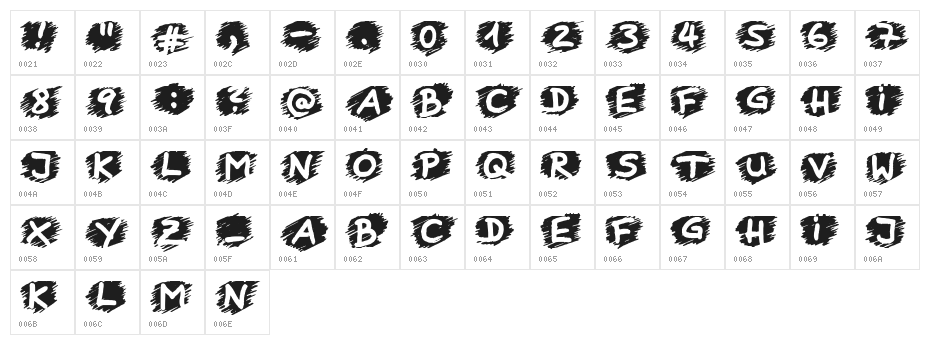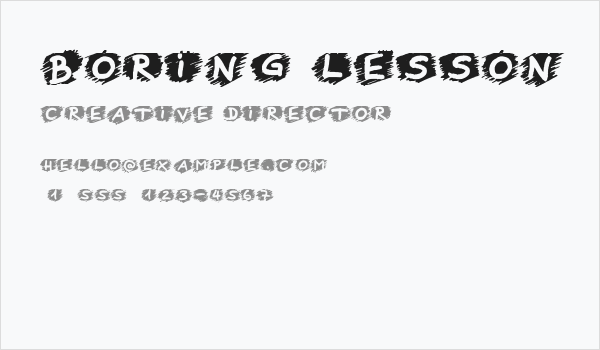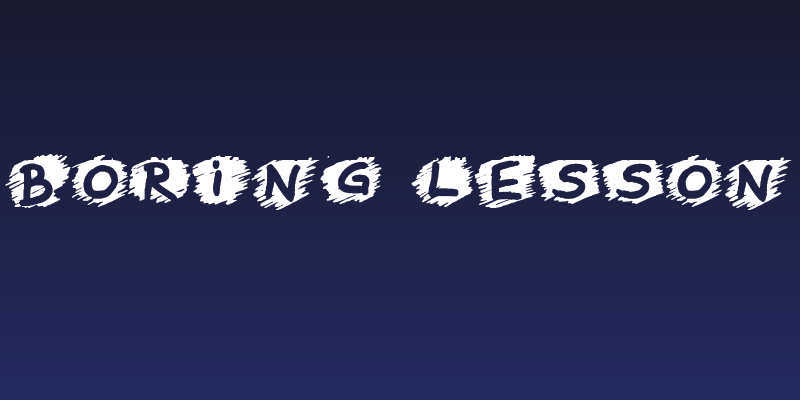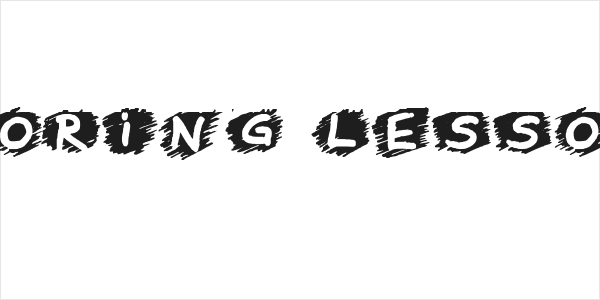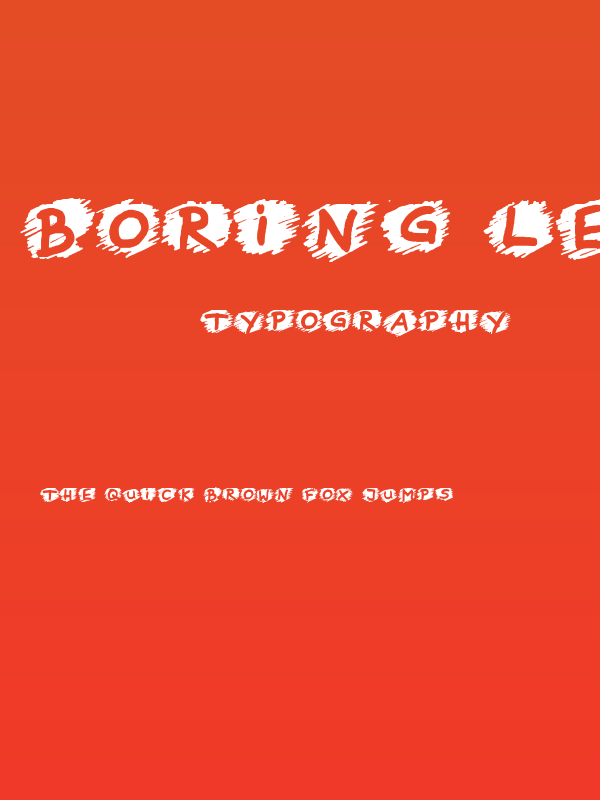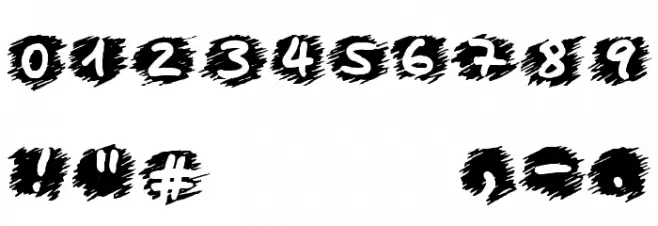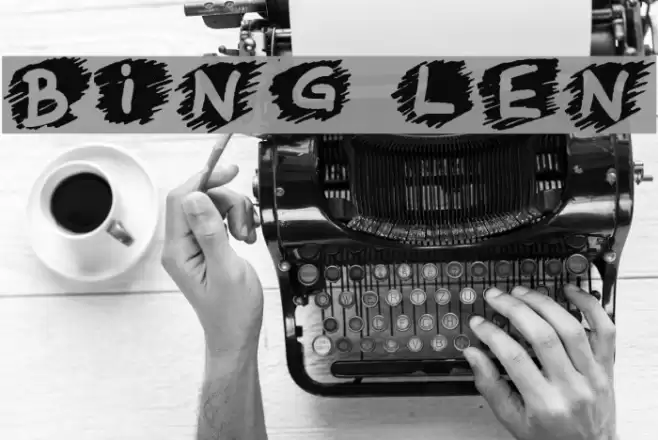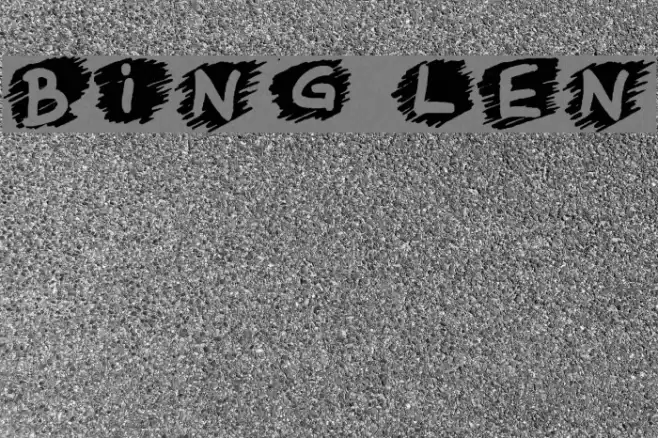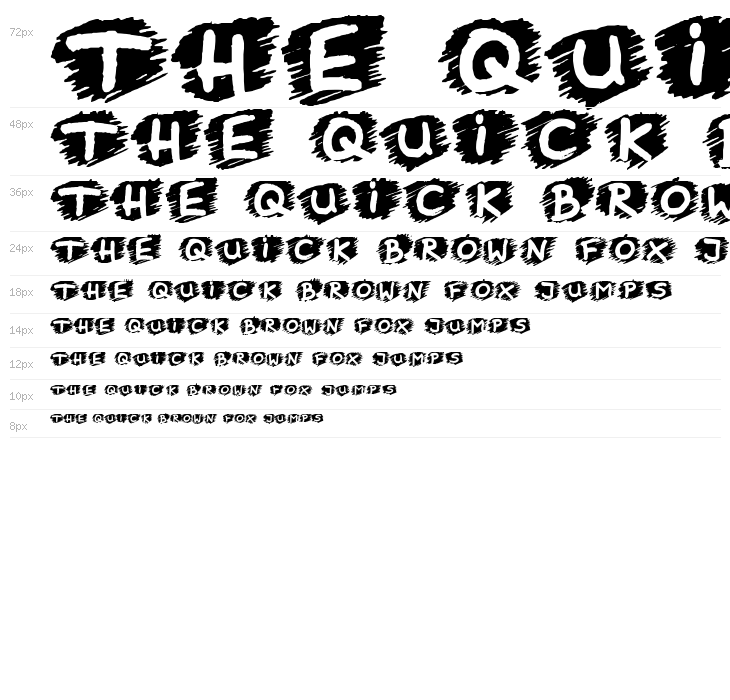
Boring Lesson Font
| النمط العام | Modern, Energetic, Edgy |
| حالة الاستخدام | Logos, Posters, Headlines |
| مشاريع مقترحة | Perfect for music album covers, skateboarding brands, graffiti art, or any project needing a rebellious, dynamic look. |